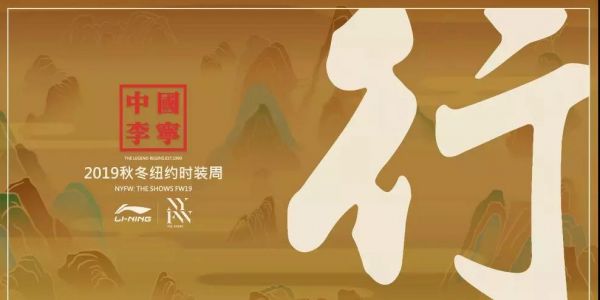
把汉字slogan、中国山水画印在衣服上,李宁“国潮”有点好看
就在我一边回味在夏威夷拍的1800张倾情写真的时候,发现了朋友圈里有好几个人发同一个不锈钢杯子的照片,说想买。
这个朴实刚硬的杯子,跟我小时候用过的一样,就是上面写着“中国李宁”四个大字,来自2019秋冬纽约时装周上的李宁秀场。
这个“中国李宁”呢,就是小时候妈妈总给我买的那个李宁。但是现在,时髦得妈都不认得了。
现在的李宁,主打的依然是运动,带些中国元素,还有些复古,颜色到廓形都漂亮到不行,看完之后,我只想说一句,我可以。
李宁这季秀的主题叫做“行”,自然是其中的一个点,它最明显的体现就是衣服的颜色。
自然的山川大河都变成了各种高级又好看的“沙漠驼”、“天空蓝”、“冰川白”拼成一件件衣服。
跳跃的荧光色也穿插在秀里面,跟简单的线条组合起来一起出现在经典的“领奖服”上。
还有参考苗族百家衣玩的拼色。
国内的著名旅游景点的“黄山”、“嵩山”和“张家界”也都被画进了这个系列里面。
它们既可以是卫衣和衬衫上冒着文人气的山水画;
也可以很现代,变成最简单的几何山峰,叠在一起,出现在毛衣、运动外套、裤子上;
还可以直接把嵩山绣在摇粒绒外套后背上,感觉背了这个,好像能变身最强的少林武僧了。
“中国李宁”这几个最有代表性的的汉字Slogan自然是少不了的,这次的字体还有图案排布都显得更考究了。
除了这些图案,中国传统的扎染也被李宁用在了这次的设计里,简单的卫衣一下子变得别致多了。
禅意十足的汉麻面料都能跟运动味十足的大口袋设计配起来,也意外的和谐。
总的来说,作为“国潮”扛把子的李宁,这次秀真的成熟多了,复古情怀和时髦度都没少,反正宇博已经看中了好几件。
说起来,李宁这几年的转型做的真的还蛮不错,在宇博的记忆中其实李宁这个品牌的变化可不止这一次。
李宁一开始就是“国货”之光,因为中国运动员终于能在领奖的时候穿自己国家的衣服了。
我记得很小的时候,李宁比起Nike和Adidas完全没差的,是我幼小心灵里想要拥有的高端运动品牌之一。
可是长大后呢,我变时髦了,李宁却没变,所以离我们年轻人也远了。我对李宁的印象,就停留在了奥运会开幕式的“番茄炒蛋“装上了。
我查了下资料,其实他们一直在认真地做各种运动产品的研发,但跟时尚没什么关系,所以也没啥声音。
去年,李宁终于改头换面,开了个“中国李宁”的线,跑到了纽约市装周上走秀,一下子就雄起了。
那次走秀还制造了些强势爆款,比如曾经一度刷屏的“悟道”鞋。
连Bella Hadid都套上印着李宁本人的T恤为他带货。
悟道也成了一个系列,有悟道R、悟道2ACE、悟道ACE+等等。
悟道R
悟道2ACE
悟道ACE+
我印象中,应该很少有国产品牌球鞋能像Yeezy一样让人上网排队抢预售的,而悟道2就做到了。
后面李宁把2019的春夏秀搬到了巴黎,这次的衣服复古味比较重,还看到体操服熟悉的身影。
总之,现在的李宁,再也不仅仅是小时候印象中的番茄炒蛋,
同时也是我这样时髦好看的年轻人都想穿的品牌了。
更重要的是,穿着“中国李宁”四个大字,感觉比胸前有个耐克勾或者阿迪三叶草,感觉更洋气呢。